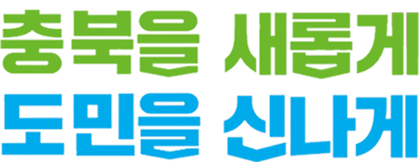
이 폰트 이름 아시나요? gml*** 2024.08.29 알려주세요! 댓글 0 등록 sta*** Sandoll 격동고딕 https://www.sandollcloud.com/font/6/Sandoll-GyeokdongGothic 을 기본으로 하고 '을' 자, '롭' 자, '신' 자처럼 아래로 뾰족하게 나온 글자들은 Sandoll 맵씨를 적용한 것 같네요. https://www.sandollcloud.com/font/271/Sandoll-Mapssi 2024-08-29 답글 달기 댓글 더보기 쉽고 빠르게 가장 비슷한 폰트를 알고 싶다면? 이미지로 검색하기
Sandoll 격동고딕 https://www.sandollcloud.com/font/6/Sandoll-GyeokdongGothic 을 기본으로 하고 '을' 자, '롭' 자, '신' 자처럼 아래로 뾰족하게 나온 글자들은 Sandoll 맵씨를 적용한 것 같네요. https://www.sandollcloud.com/font/271/Sandoll-Mapssi